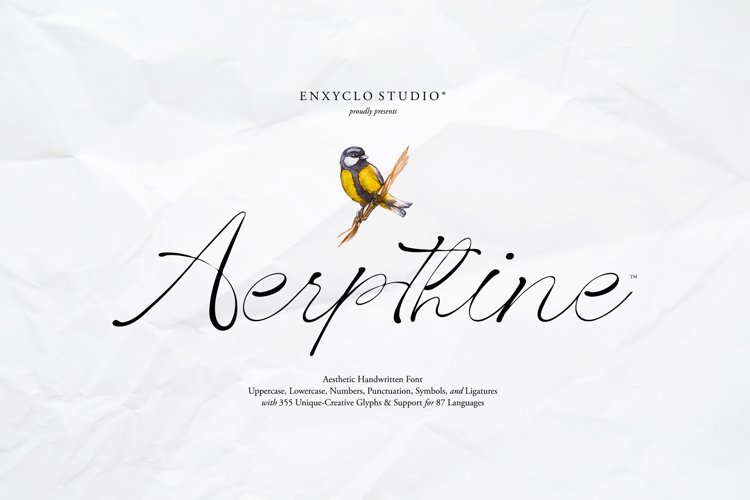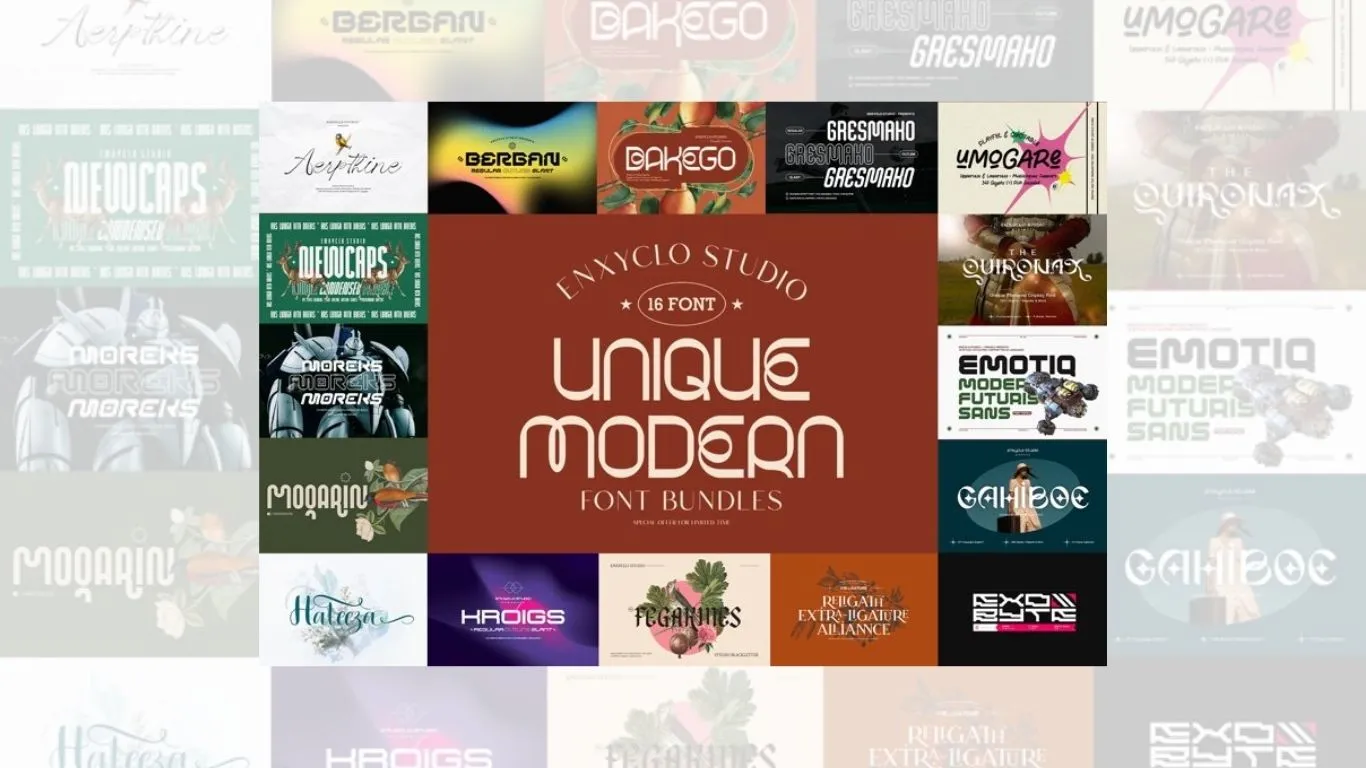
Font Bundles 每週免費字體包 Unique Modern Font Bundle Vol.01
本週免費字體:UNIQUE MODERN FONT BUNDLE – VOL.01
這套字體包由設計工作室 Enxyclo 製作,有 16 款字體。風格橫跨未來感、科技感與摩登時尚,作品在字體設計社群中頗具口碑。